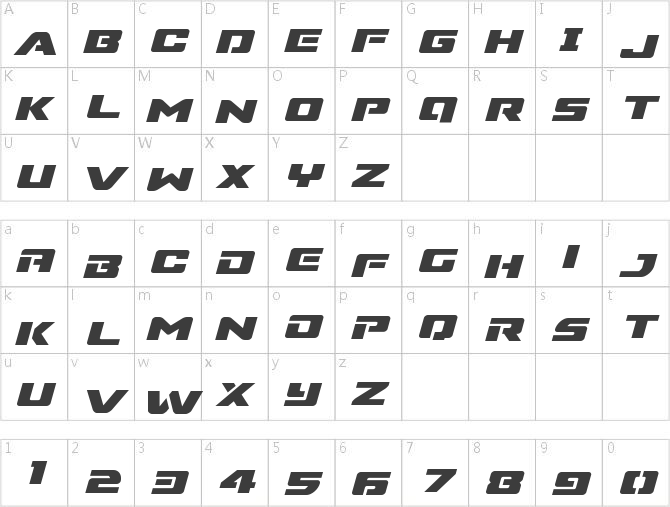
Super Commando Expanded Italic 詳情頁(yè)
Super Commando Expanded Italic字體字庫(kù)是一款讓人賞心悅目、百看不厭的英文字體,適合各類廣告和產(chǎn)品包裝設(shè)計(jì)應(yīng)用,字體大小0.03MB,格式為ttf字體,上傳用戶是董志高,作者/版權(quán)方為未知